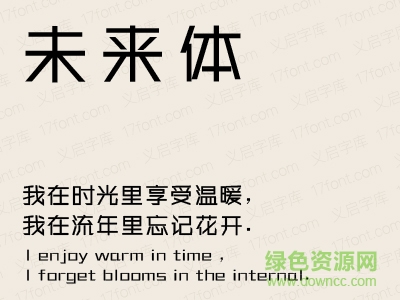
軟件介紹 軟件標簽: 義啟字體 字體 義啟未來體字體是一款漂亮的義啟字體,該字體方方正正,非常具有對稱美,可應用于廣告設計、藝術設計等多個領域,喜歡的小伙伴快來綠色資源網(wǎng)下載吧!義啟未來體字體介紹義啟未來體字體是一款用于動感設計方面的字體。該付費下載字體僅限于個人非商業(yè)用途使用,一切用于商業(yè)用途請務必購買正版授權。字體安裝方法方法一:控制面板/字體/文件/安裝新字體;方法二:直接將字體復制到C:\WINDOWS\Fonts。方法三:針對win7系統(tǒng),用戶只需選中字體右鍵安裝即可。 軟件截圖 上一張下一張(1 / 1) 安裝詳細截圖 猜你喜歡 商業(yè)字體 義啟字體 商業(yè)字體是應用在商品包裝、平面設計、影視設計、雜志報刊、印刷排版等領域的字體,涵蓋了柔美的、古韻的、現(xiàn)代感等不同風格的字體,可適用于各種商業(yè)領域! 查看更多>> hiragino sans gb w6字體 10.15M/中文/7.0/下載 hiragino sans gb w3亮體 16.60M/中文/3.8/下載 電腦字體奇思楷體 2.92M/中文/10.0/下載 ubuntu字體合集 1.68M/中文/6.0/下載 universltstd英文字體 23KB/中文/10.0/下載 roboto字體 991KB/中文/10.0/下載 義啟字體 義啟字體是義啟家族(17font)推出的一系列字體合集,包括了很多類型,如:義啟粗楷體ttf、義啟萌妹體、義啟明星字體等,每款字體都很有特點,當然,也很漂亮,很多朋友都喜歡使用義啟字體,趕快收藏起來吧! 查看更多>> 義啟風尚黑字體 842KB/中文/0.0/下載 義啟星空之翼ttf 782KB/中文/10.0/下載 義啟奶萌小小喵字體 1.31M/中文/0.0/ttf版下載 義啟戀上桃花拼音字體 1.29M/中文/5.0/ttf免費版下載 義啟小南同學字體 437KB/中文/5.0/ttf免費版下載 義啟為你心動字體 592KB/中文/6.6/ttf免費版下載 其他版本下載 標題 大小 更新日期 下載 義啟簡圓體ttf 1.41M 2018-05-09 下載 義啟心花怒放 ttf免費版 2.42M 2017-02-13 下載 義啟橙嘖嘖體 ttf免費版 1.80M 2017-02-13 下載 義啟中秋體字體 ttf免費版 3.59M 2018-04-07 下載 義啟月亮體 2.40M 2017-02-15 下載 義啟顏值體字體 2.40M 2017-02-15 下載 義啟春暖花開體 2.16M 2017-03-07 下載 義啟遇見體字體 10.00M 2017-08-16 下載 義啟星空之翼ttf 782KB 2019-03-22 下載 下載地址 電腦版 義啟未來體 免費版 點擊報錯 軟件無法下載或下載后無法使用,請點擊報錯,謝謝! 關閉報錯反饋 請描述您所遇到的錯誤,我們將盡快予以修正,謝謝! *必填項,請輸入內(nèi)容 本類最新 dreamweaver字體庫 首爾南山體字體 v1.06 官方版 潮字社風云簡ttf 潮字社凌渡鯤鵬簡體字體 潮字社曾玉波手書簡字體 微博慧心字體 相關文章 Photoshop字體安裝使用方法和技巧 如何解決“無法新增字體”問題 Win 7系統(tǒng)安裝字體方法 網(wǎng)頁字體大小設置方法 怎么改網(wǎng)頁字體大小 在Linux系統(tǒng)中安裝字體的幾種方法 windows7字體顯示問題:打開某些程序的時候顯示的是亂碼 用戶評論 熱門評論 最新評論 發(fā)表評論 查看所有評論(0) 昵稱: 請不要評論無意義或臟話,我們所有評論會有人工審核. 字數(shù): 0/500 (您的評論需要經(jīng)過審核才能顯示)